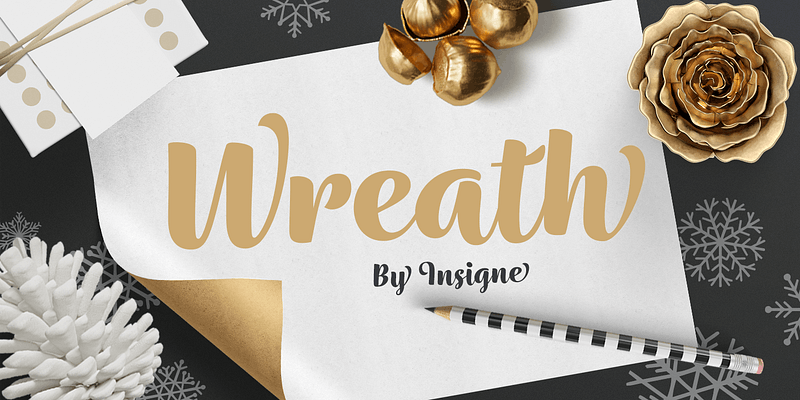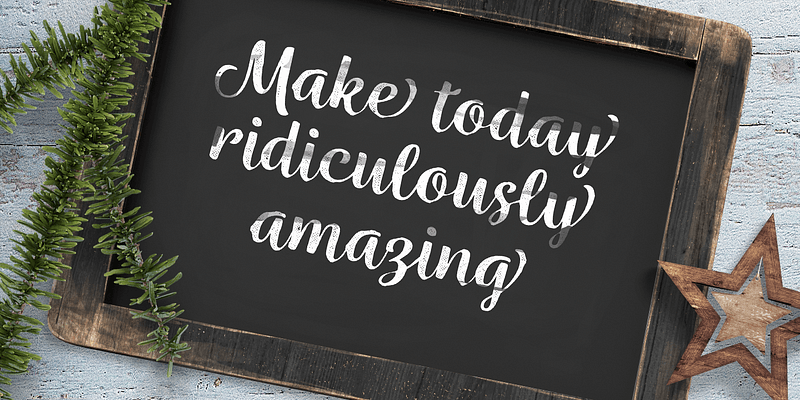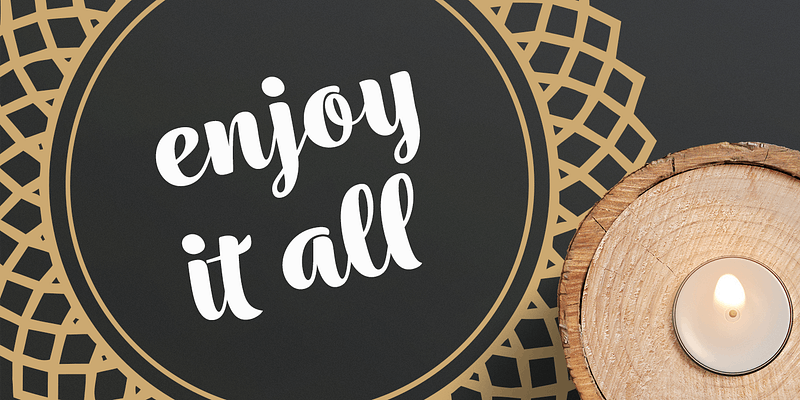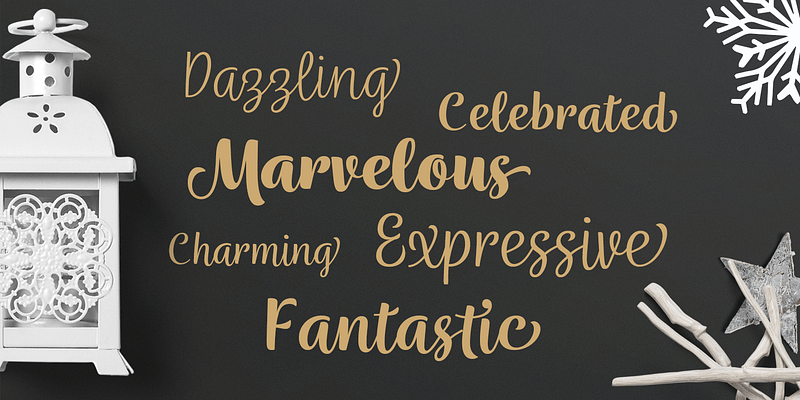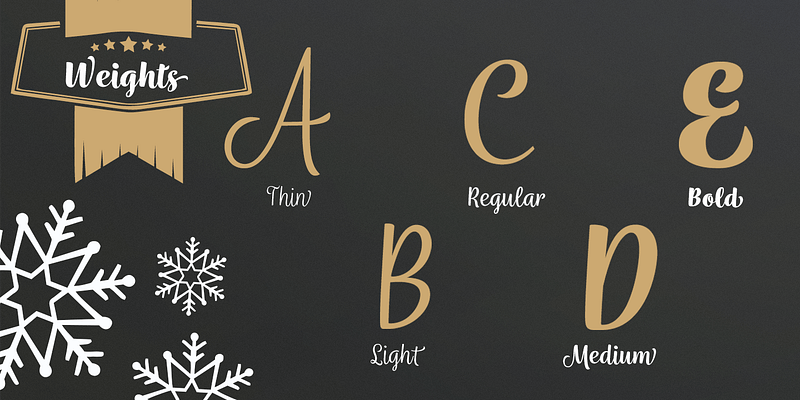
Wreath ist eine Schriftart, die mit einem spitzen Pinsel gezeichnet wurde. Entworfen von den Elfen der insigne Werkstatt, wurden seine einzigartigen Formen geschaffen, um Ihre Geschenketiketten zu verschönern.